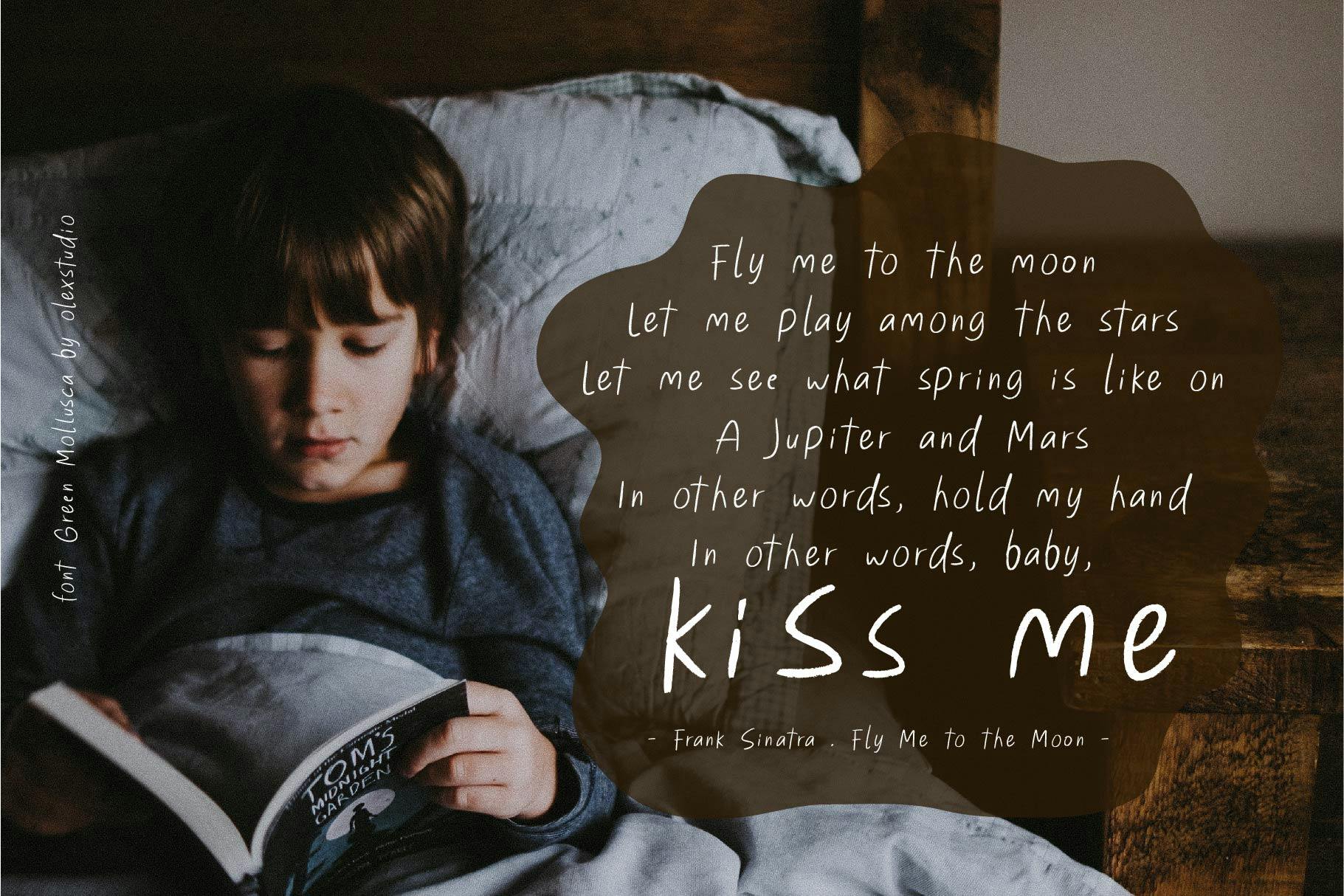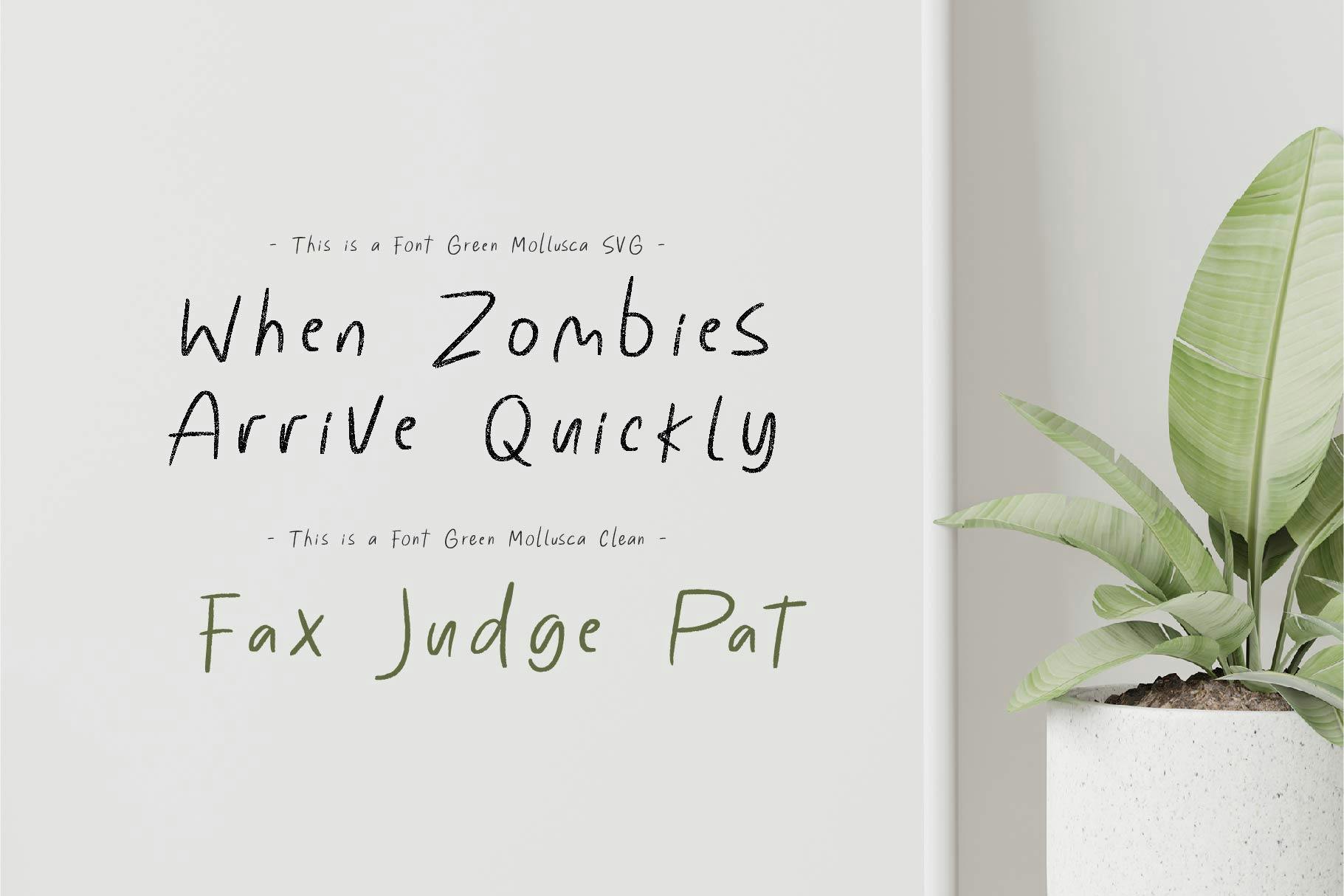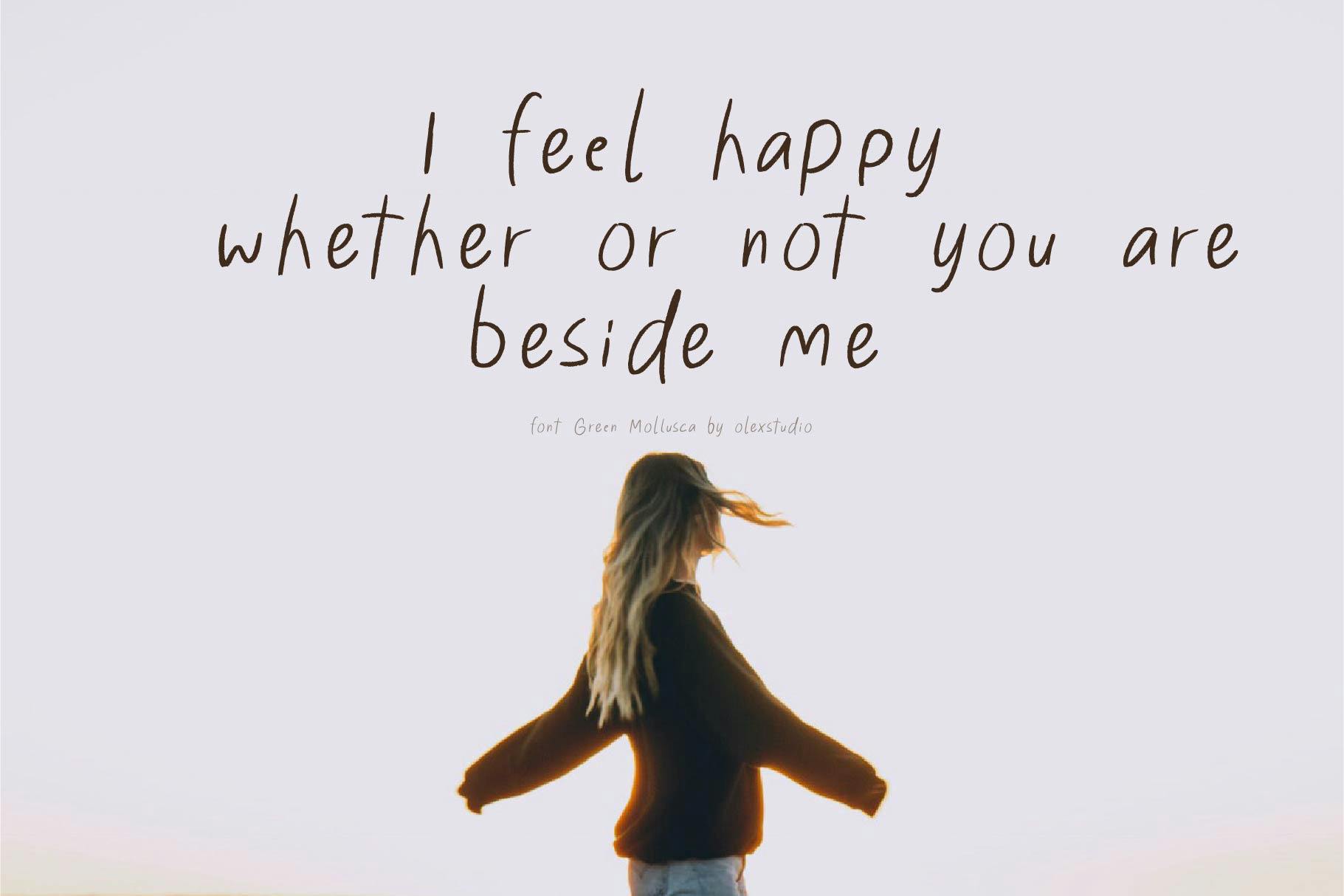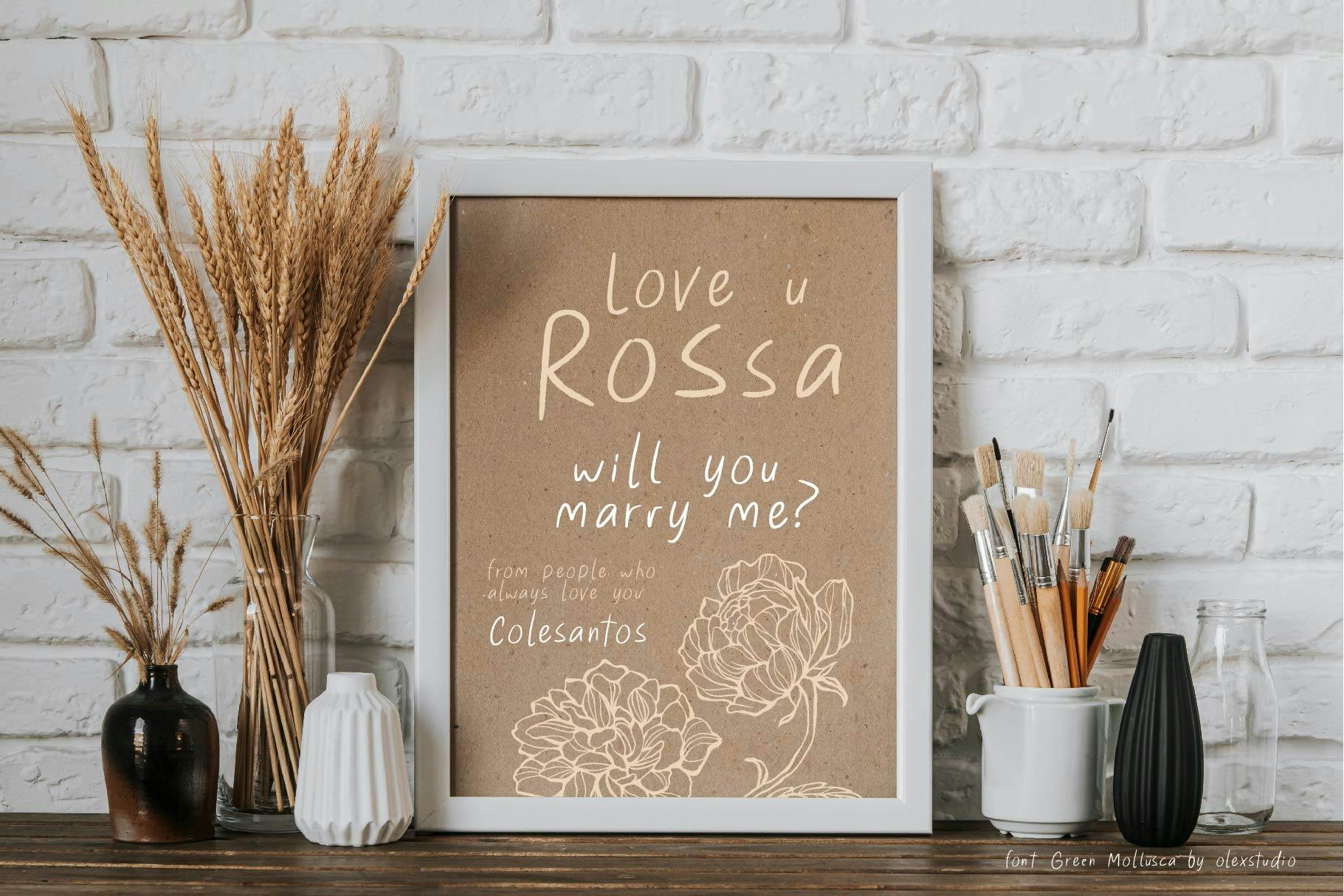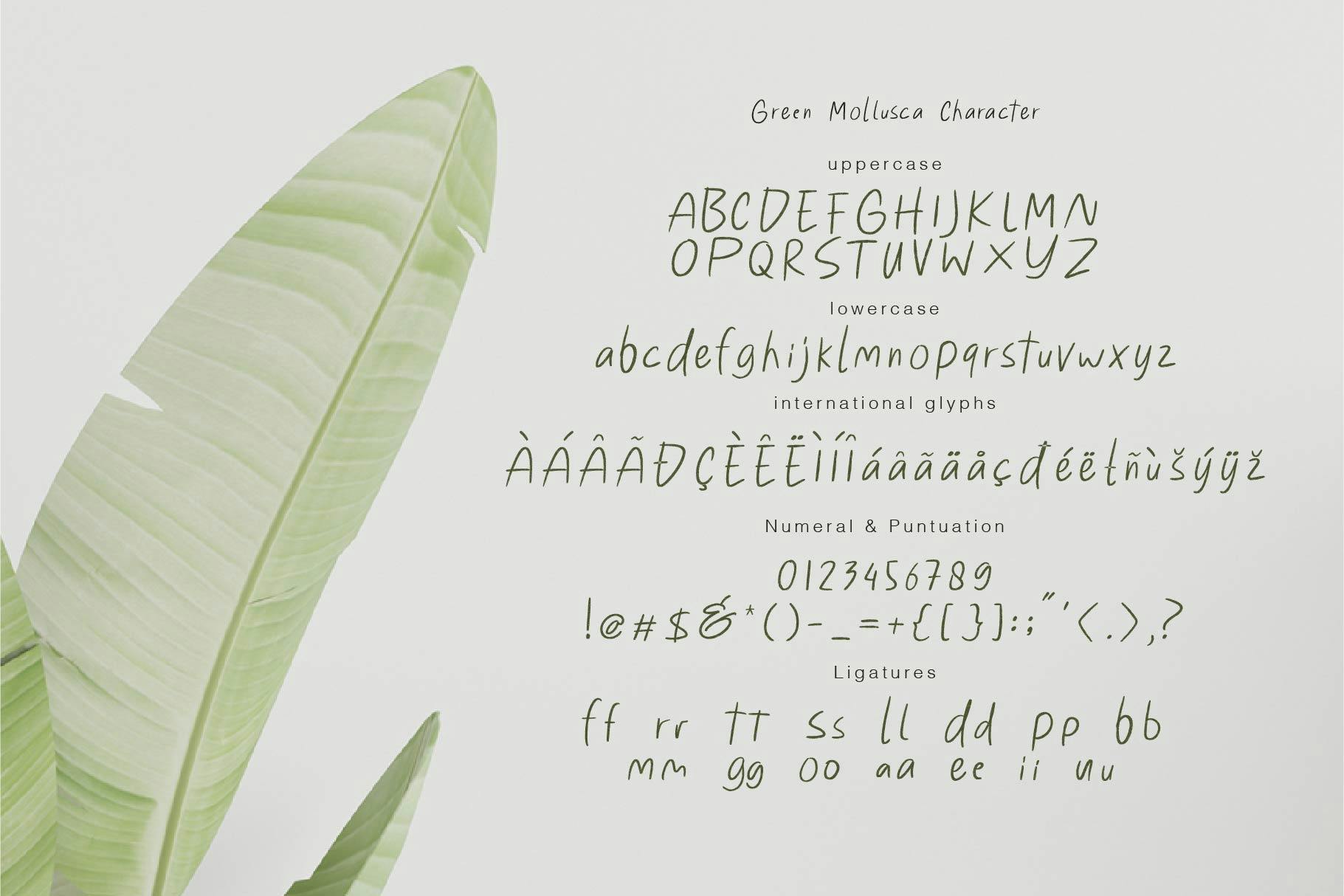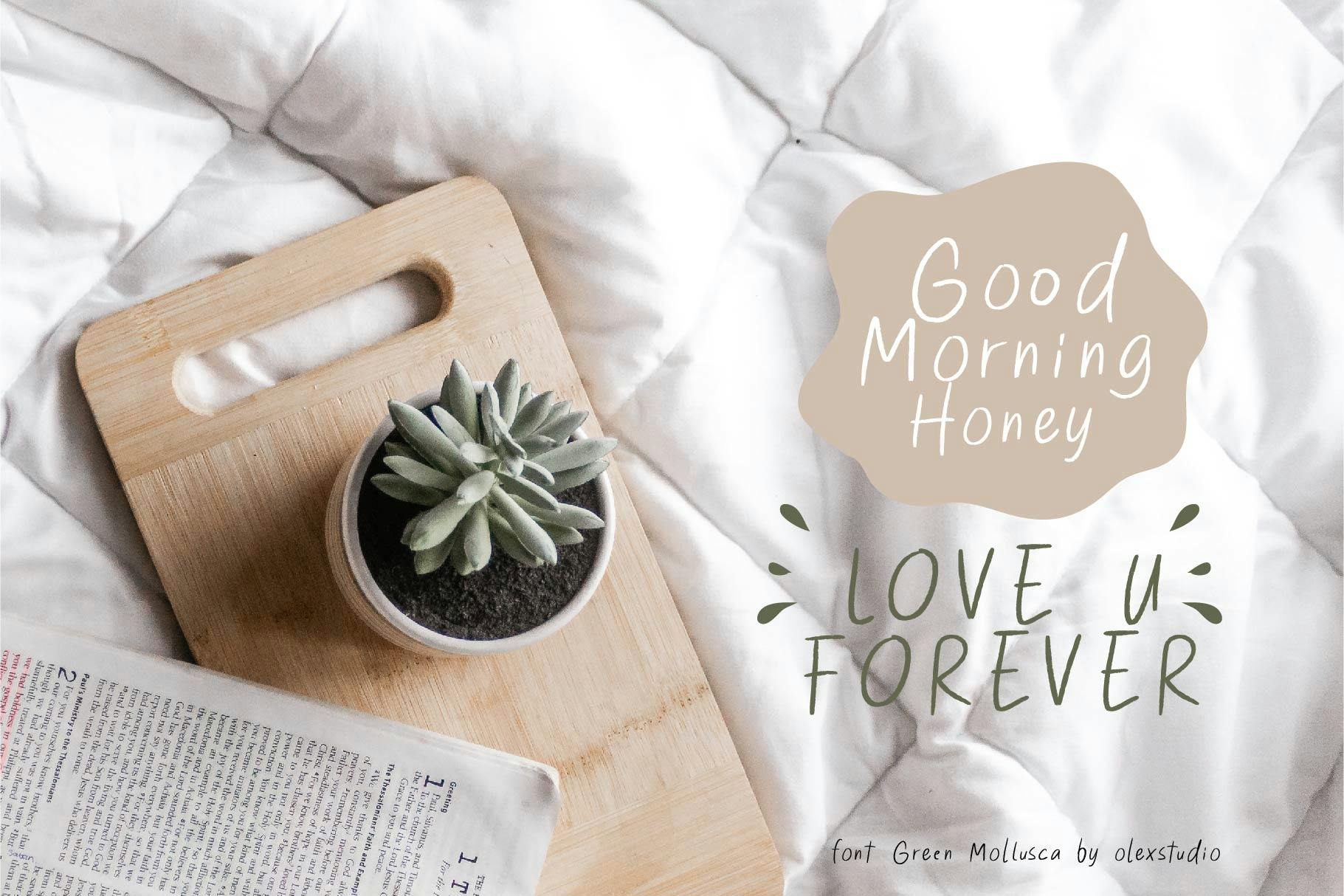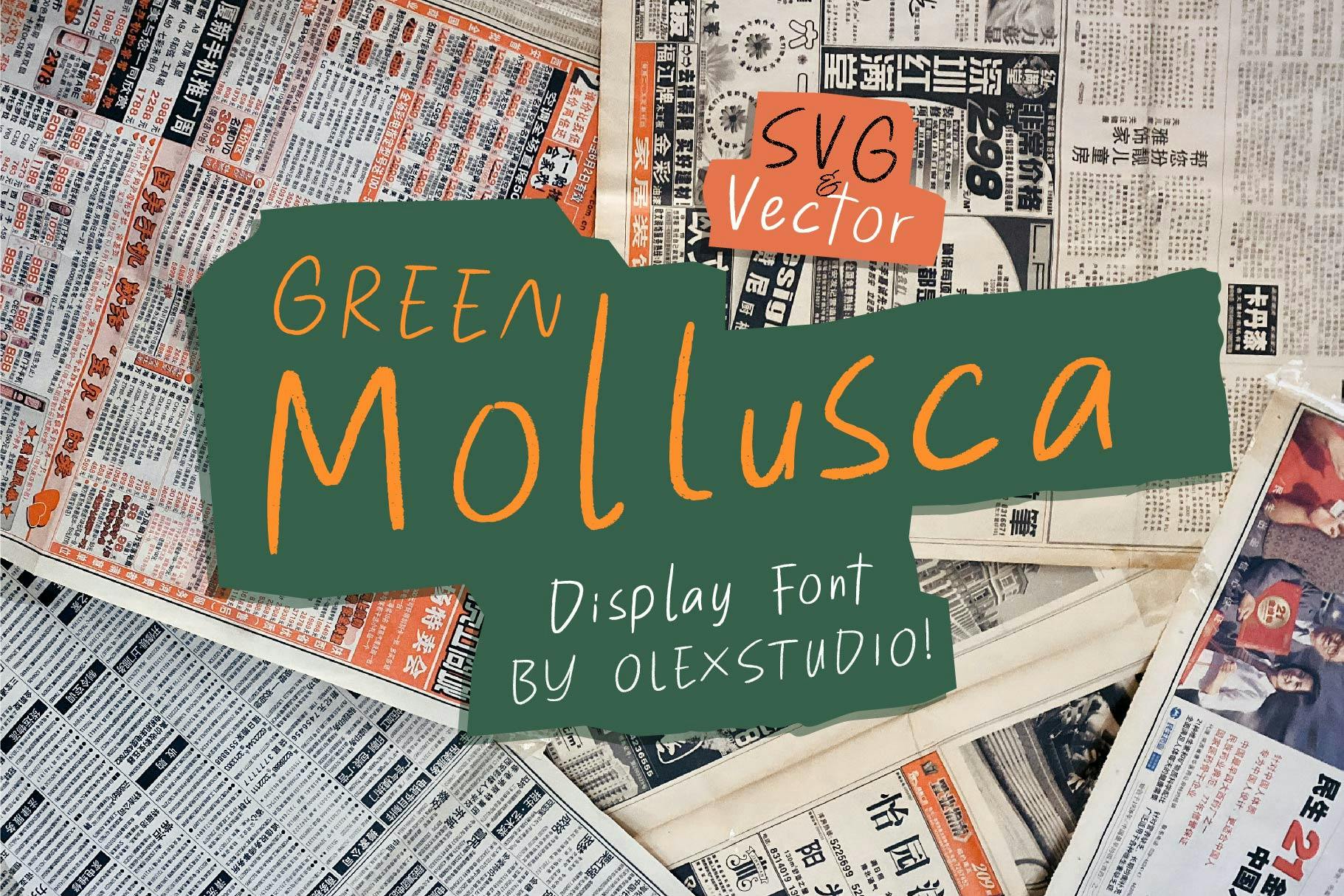
فونت گرین ملوکسا - فونت نمایش، بر روی تمامی طراحیهای شما از جمله دعوتنامهها، طراحی پوستر، طراحی کتاب، مواد برندینگ، لوگو و سایر پروژههای طراحی فوقالعاده زیبا به نظر میرسد.
فونت گرین ملوکسا - فونت نمایش شامل کاراکترهای استاندارد، حروف کوچک و بزرگ، اعداد، نشانهگذاری، لیگاتورها و گلیفهای بینالمللی است. شما فایلهای OTF، TTF و WEBFONT را دریافت خواهید کرد که شامل فونت SVG و فونت وکتور نیز میشود.